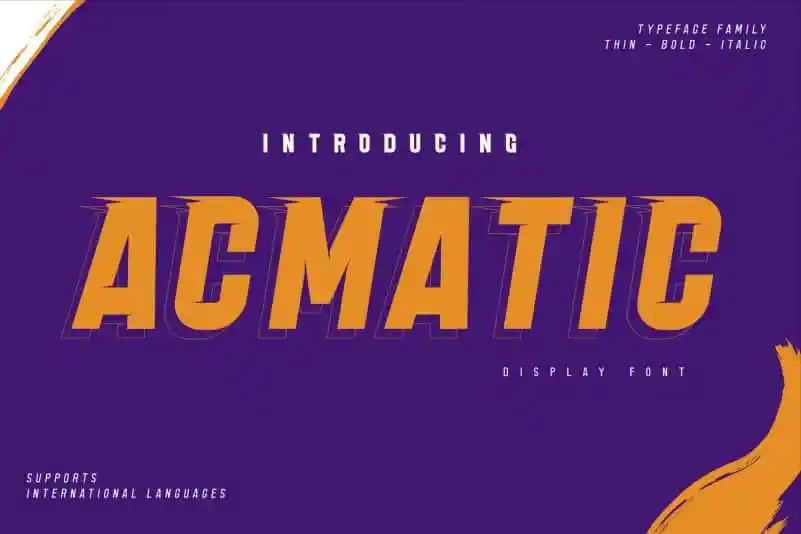
Acmatic Display Font – Fonte Grátis
Acmatic Display Font
A acmático Display Font foi criada para atender às necessidades dos projetos que exigem beleza e originalidade. Trata-se de uma fonte de display que oferece um toque moderno e inovador, ideal tanto para aplicativos digitais quanto para materiais impressos. Com linhas simples e elegantes, a acmático traz uma presença visual forte e diferenciada aos seus projetos. Perfeita para criar uma identidade gráfica única, este design de fonte de display de qualidade é um ótimo recurso para qualquer designer que busca tornar seu trabalho ainda mais marcante e autêntico.